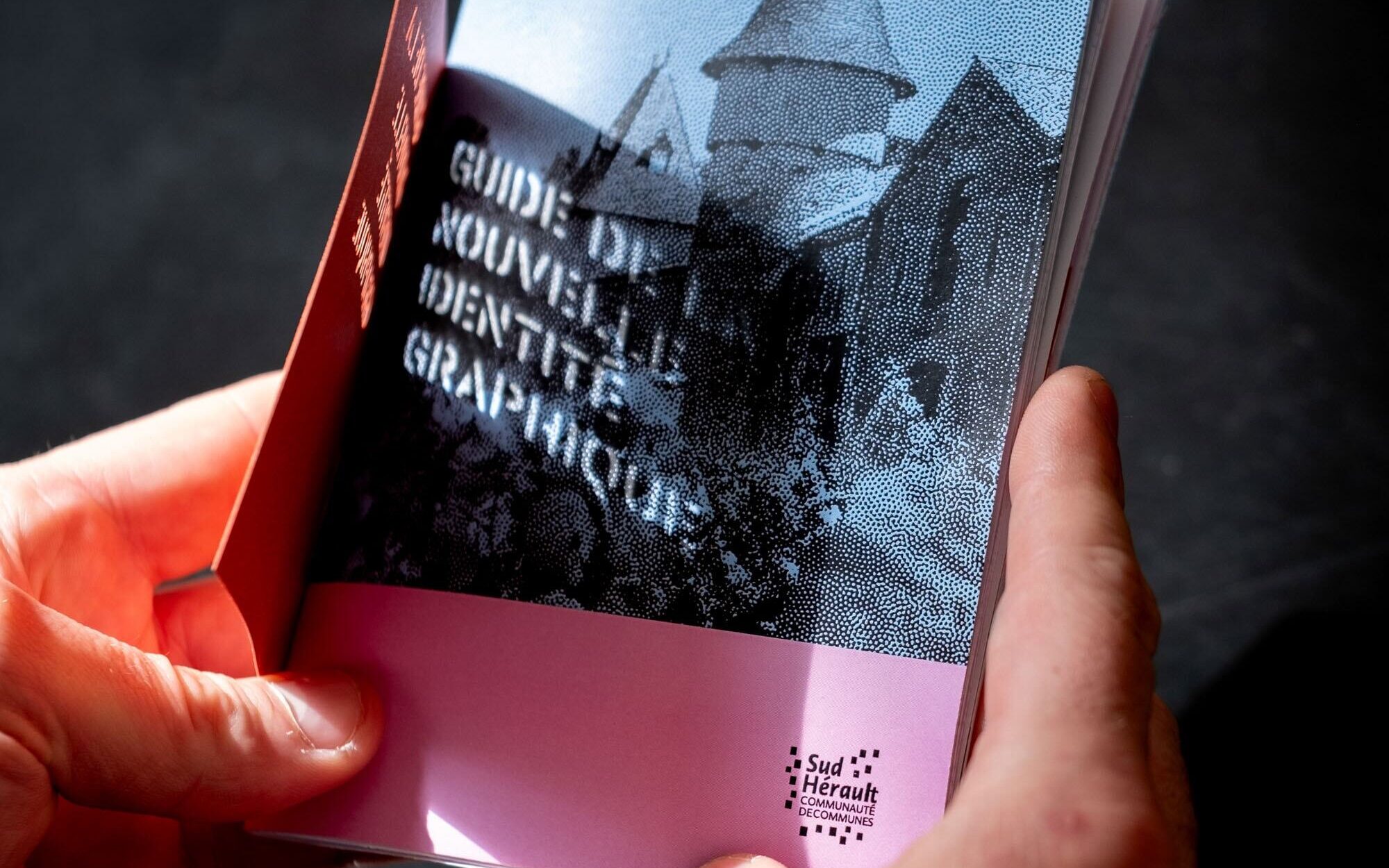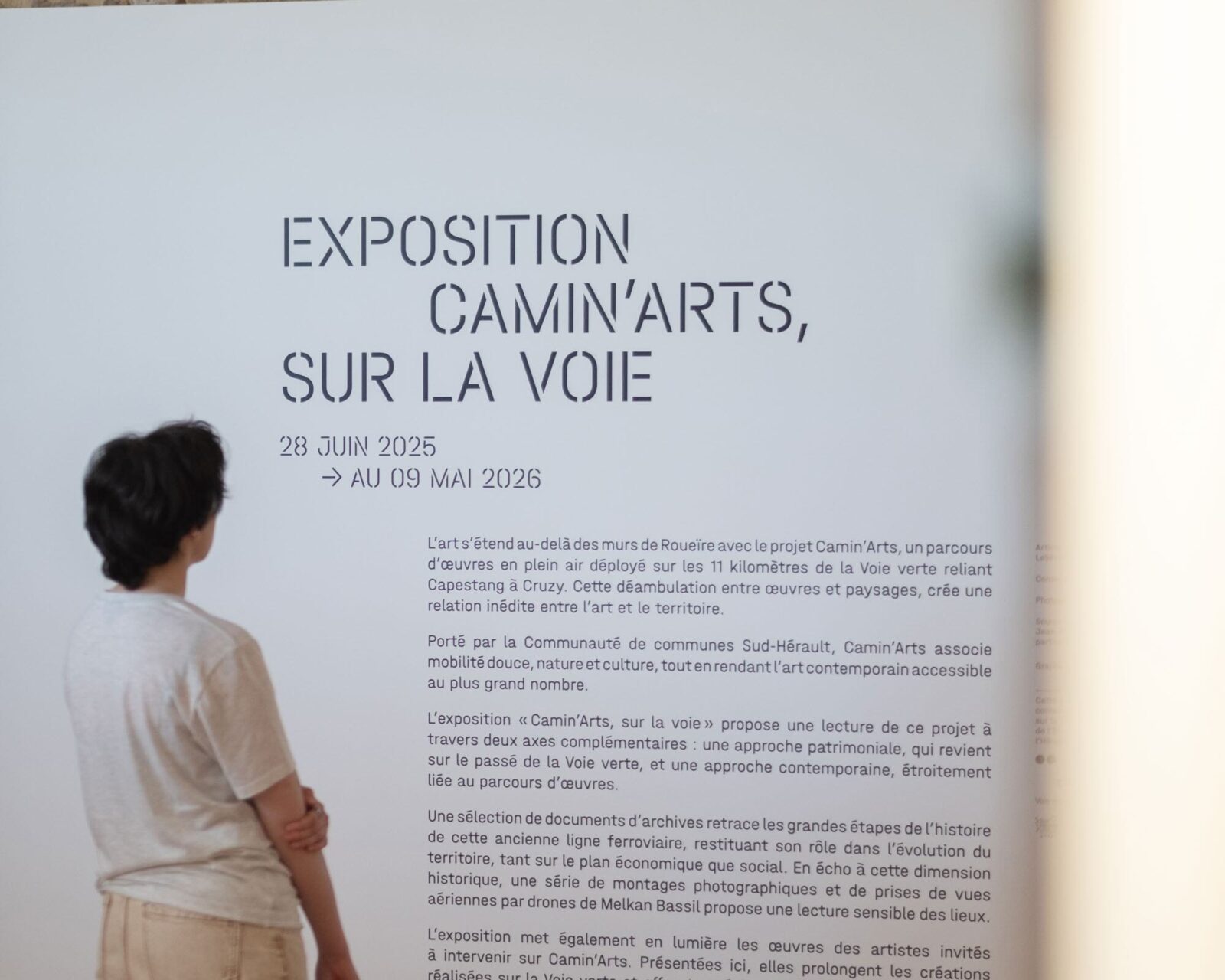
Halvar Stencil erweitert das Halvar-Universum, indem es auf dessen konstruierten Basis aufbaut: Die solide Schablonenschrift ist eine Schrift für Baustellen, Kraftwerke, Transportbehälter und alles, was visuelle Wirkung erfordert.
Durch die Zerlegung der Buchstaben in einzelne Bestandteile wird Halvars Ingenieur-Attitüde besonders deutlich. Halvar Stencil ist eine praktische Schrift, konstruiert aus kreisförmigen und rechteckigen Elementen, deren roher Charakter durch Konsistenz und solide Verarbeitung harmonisiert wird. Von kräftigen Schriftgewichten, die sich für den flächigen Einsatz eignen, bis hin zu feinen Schnitten - Halvar Stencil ist flexibel und passt sich den Wünschen des Nutzers an.
Das Multiscript-Design der Halvar Stencil umfasst das griechische, lateinische und kyrillische Alphabet, was ein marktübergreifendes Branding ermöglicht. Natürlich ist das umfassende System auch mit Tabellenziffern, hochgestellten Ziffern, lokalen Varianten sowie vielen anderen nützlichen OpenType-Funktionen ausgestattet.
Ergänzend dazu bietet Halvar mit seiner Duplex-Funktion die Möglichkeit, Texte in komplexen Umgebungen aufzuhellen oder zu verdunkeln, ohne dass sich der Nutzer Gedanken über die optische Textstruktur oder verzerrte Umbrüche machen muss. Wie Halvar hat auch Halvar Stencil eine absolut gleichmäßige Zeichenbreite über alle Gewichte hinweg.
Strukturiert in eine ausladende Breitschrift mit kräftigen Statur, eine moderate Mittelschrift und eine kompakte Engschrift mit schlanken Buchstaben, hat jede Subfamilie neun Stile, die von hauchfeinen Haarlinien bis hin zu massiven und dunklen Gewichten reichen. Diese drei Familien – vereint in der Halvar Stencil SuperFamily – decken eine Vielfalt von Facetten ab.
Darüber hinaus hält die Havar Stencil drei optische Größen für die Breiten der Stege bereit. So kann zwischen einem engen MinGap, einem mittleren MidGap und einem großen MaxGap ausgewählt werden. Damit ist sichergestellt, dass Halvar Stencil für jeden Auftrag die optimale Nuance an stencilness zur Verfügung steht – ganz egal ob die Schriftart als großflächiger Druck auf einem Container oder eher kleinteilig als Plakette verwendet wird.
Der Variable Font der Halvar ermöglicht mehr als nur deren Konfiguration von Gewicht und Breite: Durch eine manuelle Skalierung kann die Stärke der Schablonen-Stege stufenlos sowie individuell angepasst und getestet werden.